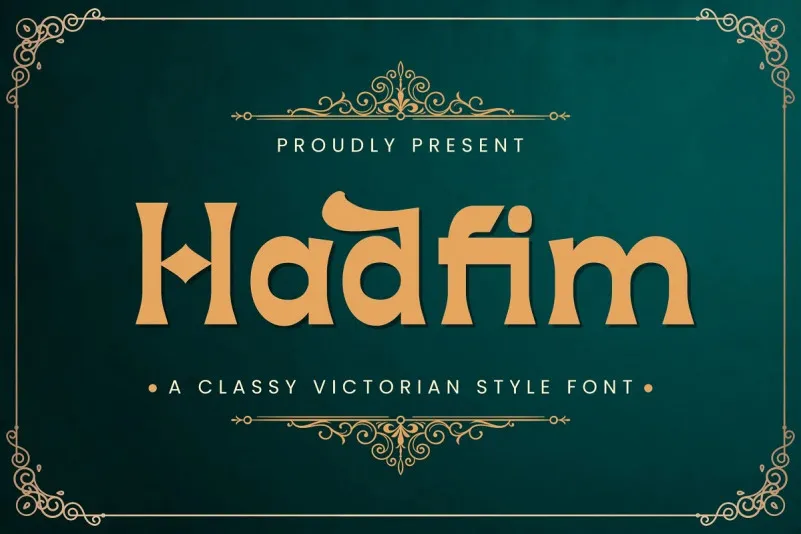
Hadfim Serif Font – Download Grátis
A Hadfim Serif Font é uma criação inspirada nas antigas sinalizações e selos das cervejarias, com um toque vintage victoriano que enriquece qualquer layout de texto. Seu design elegante e sofisticado faz dela uma escolha ideal para ambientes onde se busca um equilíbrio entre clássico e contemporâneo. Esta fonte serifa não apenas complementa textos em sites, revistas ou publicações, mas também ganha destaque quando usada em materiais impressos como cartazes, flyers ou embalagens de produtos. A Hadfim é perfeita para quem busca um toque nostálgico sem sair do mundo moderno, oferecendo uma opção única e atraente. Engane-se se pensa que esta fonte apenas combina com ambientes comerciais: sua elegância também torna-a uma escolha ideal para arquitetura e design gráfico de arte contemporânea.